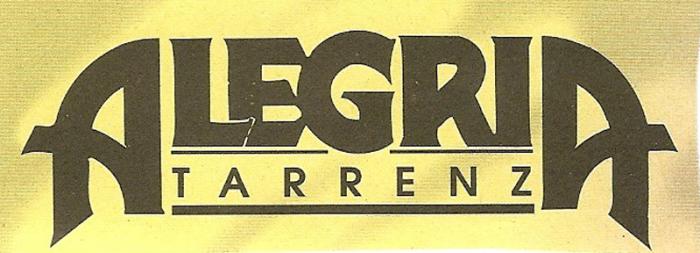
Retro-Schriftzug eines Musikcafés
gesucht wird der Schriftzug "Alegria" (nicht der Untertitel :-) )
Die Buchstaben sind modifiziert, schon klar - aber welches war die Ausgangsschrift...???
Sieht verdammt nach Fotosatz aus. Ähnlich ist die Astley aber nachdem ich jetzt ein paar Fotosatzbücher durchgesucht und nichts passendes gefunden habe, könnte ich mir auch vorstellen das die Schrift extra für das Logo gezeichnet wurde. Das R sieht jedenfalls danach aus, das gäbe es so kaum in einem Font.
Ich wundere mich immer wieder, mit welcher Selbstverständlichkeit hinter jeden Text-Logo ein Font vermutet wird.
Ich wurde selbst bei meiner Schrift Xayax gefragt, welche Schrift dort zu grunde lag, als ob es wirklich so schwer ist, so etwas komplett, und mit etwas Übung auch mit der Hand, bestenfalls mit Lineal und Zirkel, Burmester Kurven und Radien-Schablonen zu zeichnen.
Wie wichtig diese einst waren, zeigt diese Auswahl:
ich selbst besitze auch noch eine aus der Schaffenszeit meiner Mutter, und habe sie in den späten 1970 bis späten 1980er Jahren selbst oft verwendet.
Hier noch was handgezeichnetes: